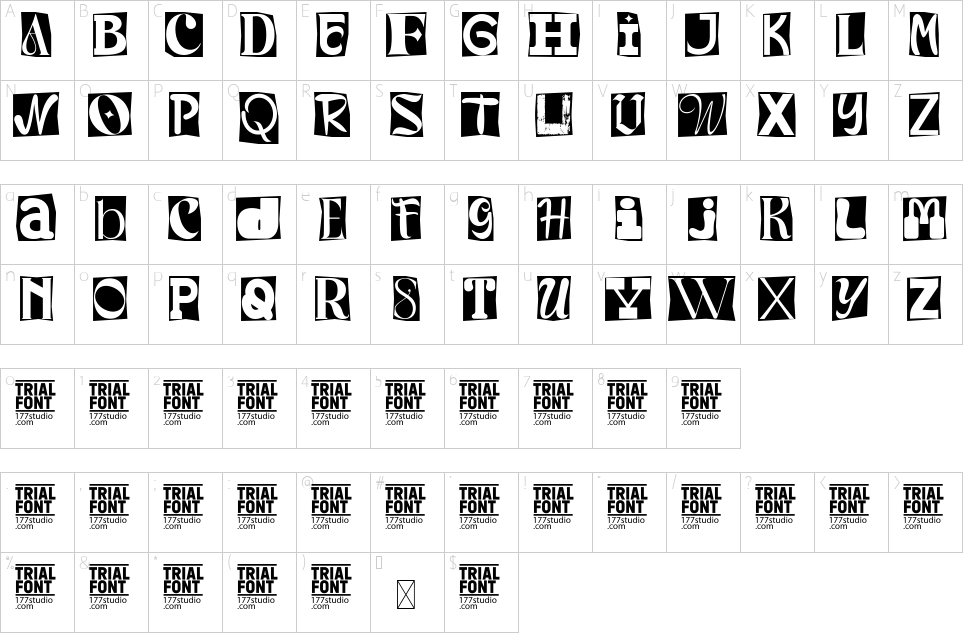
Anatomy History Font
A fonte ‘Anatomy History’ é uma seleção atraente e bem projetada para os designadores de todo o mundo. Especialmente indicada para descrições históricas ou médicas, esta fonte é uma escolha inteligente para qualquer projeto que necessite de uma tipografia elegante e profissional. Ela foi criada pelo designer desconhecido de 177studio.com e já foi baixada por 292 pessoas. Seja para criar um layout completo, um logo, ou até mesmo para uma simples assinatura, ‘Anatomy History’ é uma escolha agradável. Com uma aparência clara e detalhada, é perfeitamente adaptável para uso em qualquer plataforma, seja Windows ou Mac. Por que esperar? Baixe agora e experimente a qualidade deste design.